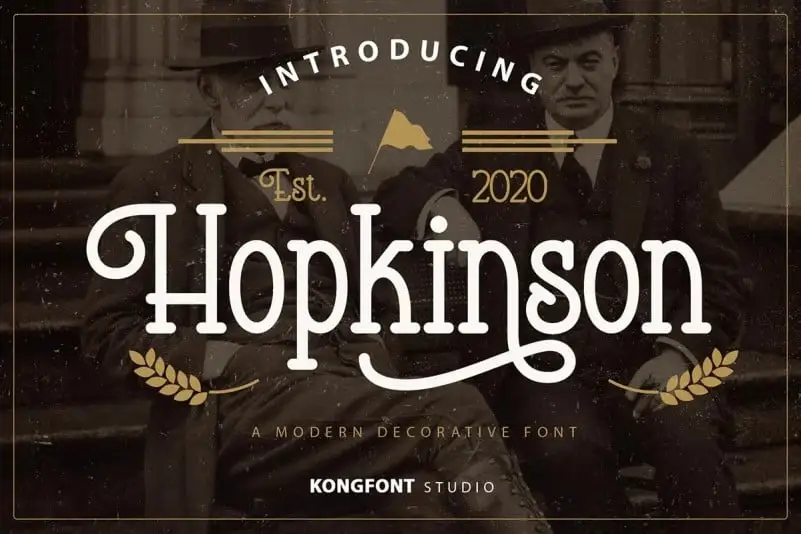
Hopkinson Display Font – Download Grátis
A fonte Hopkinson Display é inspirada num estilo vintage display que evoca a sensação de um design antigo, clássico e criado à mão. Esse tipo de fonte traz uma atmosfera nostálgica e sofisticada, perfeitamente adequada para projetos em grande escala como logotipos, banners, embalagens de produtos ou até mesmo postagens nas redes sociais. Perfeito tanto para trabalhos visuais como criações digitais, a font Hopkinson é uma escolha ideal para qualquer projeto que exija um toque delicado e autêntico do tipo tipográfico. Seja no design de embalagens, na arte fotográfica, nas etiquetas dos produtos ou até mesmo nos anúncios e cartões de visita, Hopkinson vai dar o tom certo, tornando qualquer projeto único e marcante. Com seu estilo vintage clássico e sua influência em trabalhos manuais, a font Hopkinson oferece uma maneira criativa de incorporar elementos de arte à sua identidade visual. Ideal tanto para empresas quanto para designers independentes que procuram dar um toque especial aos seus projetos digitais ou impressos, essa fonte será um recurso valioso em qualquer biblioteca de fontes.